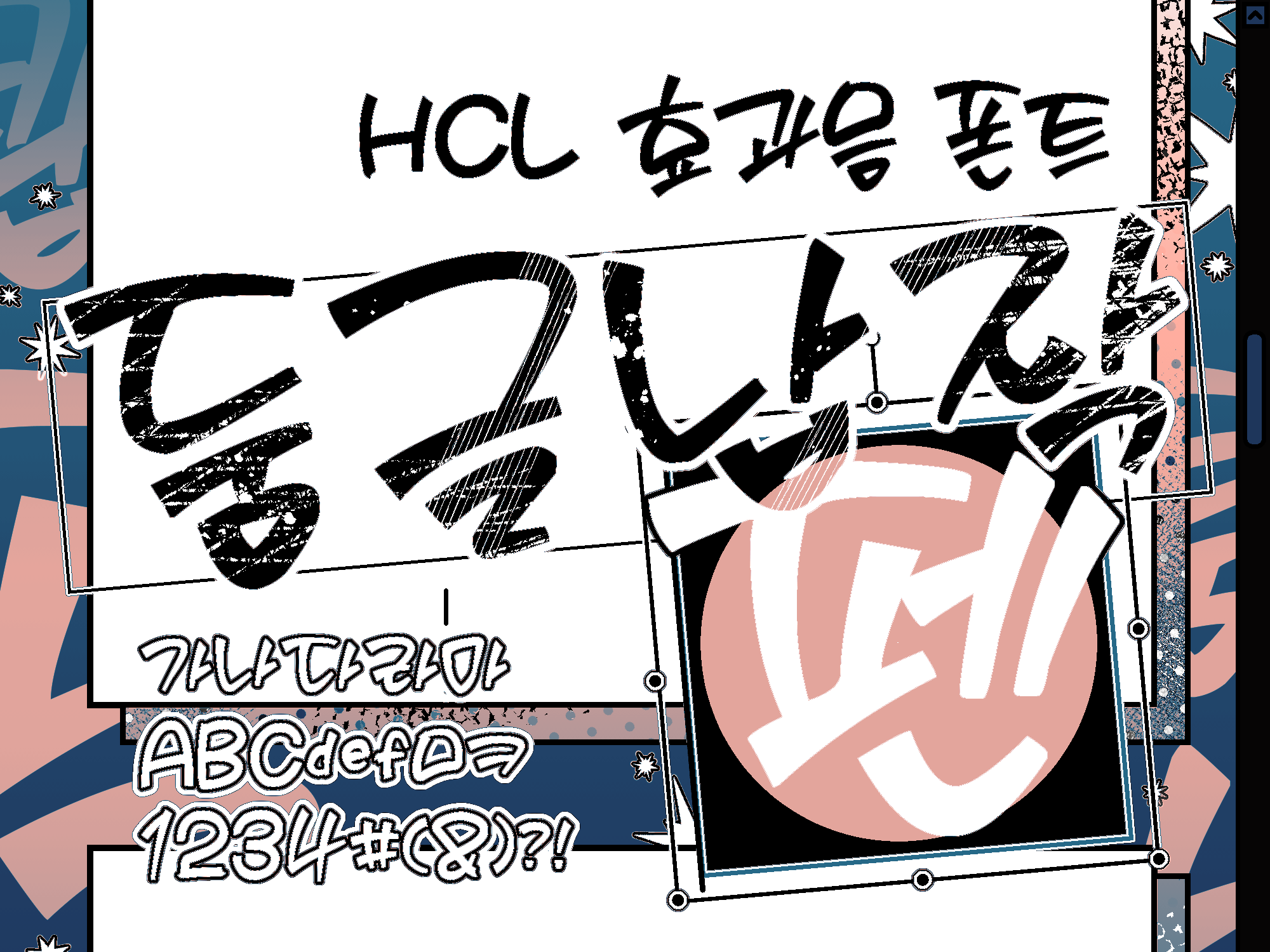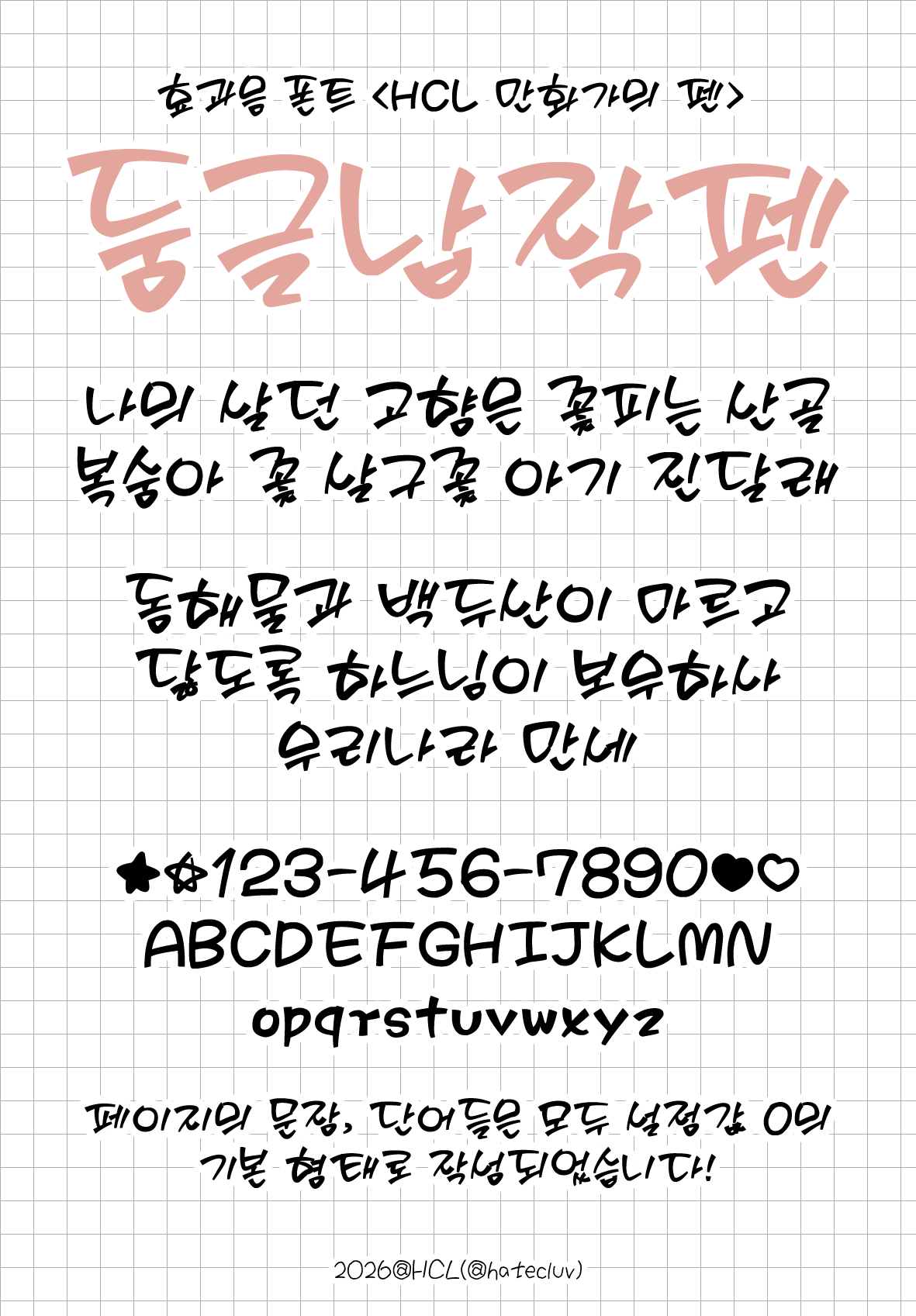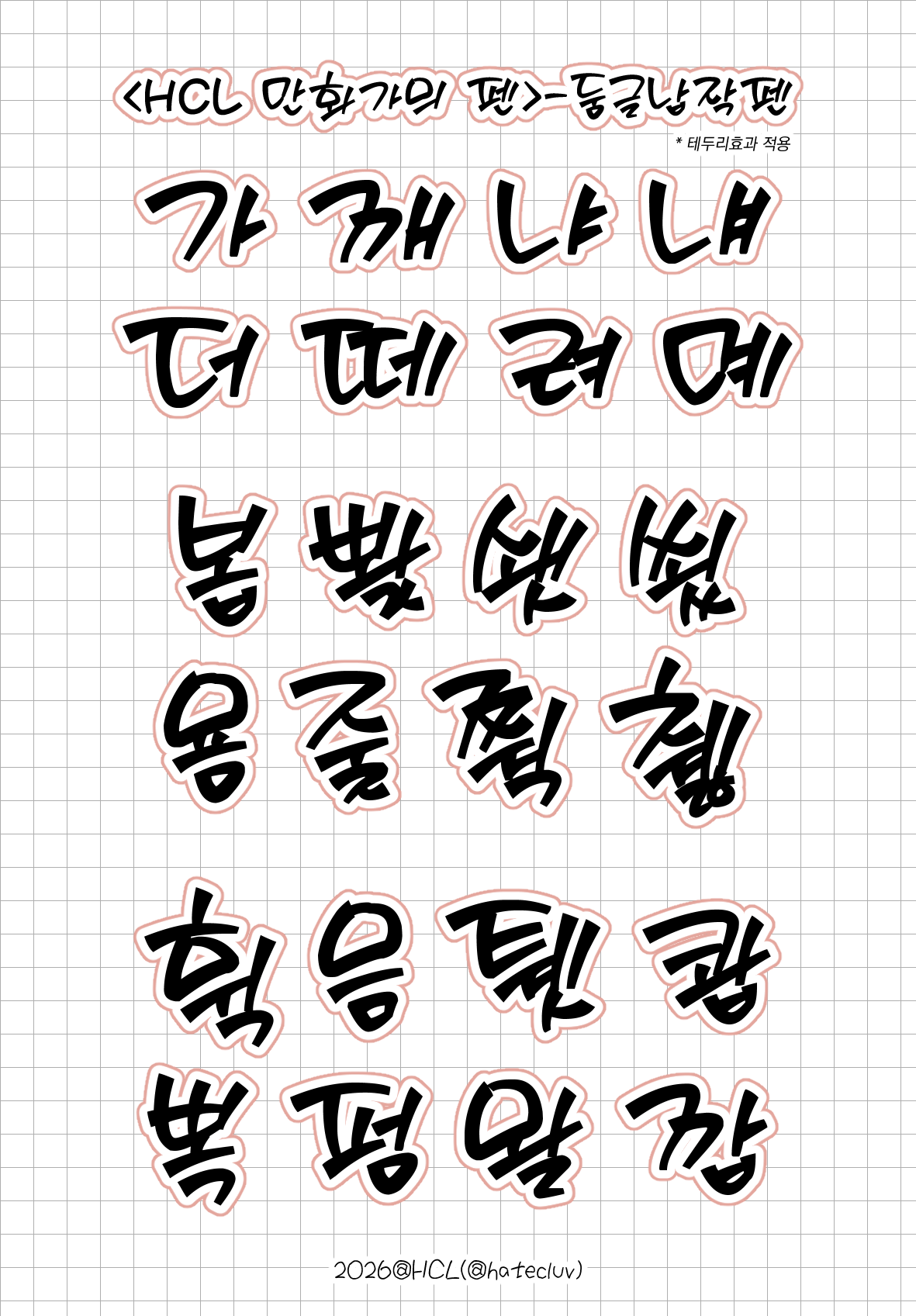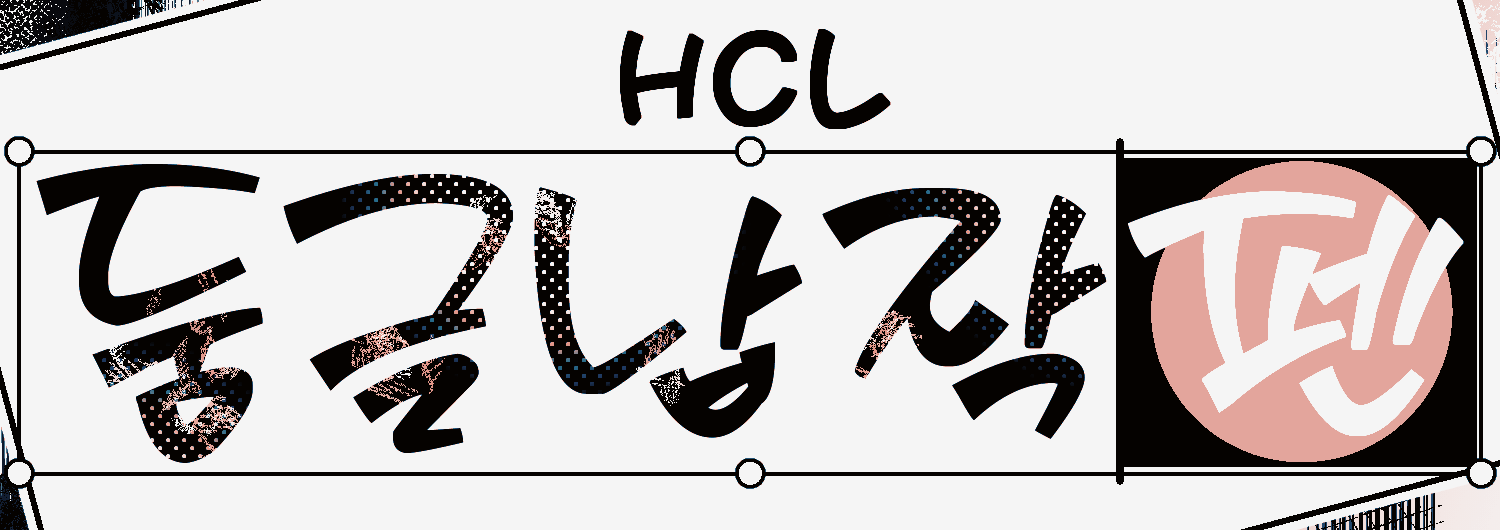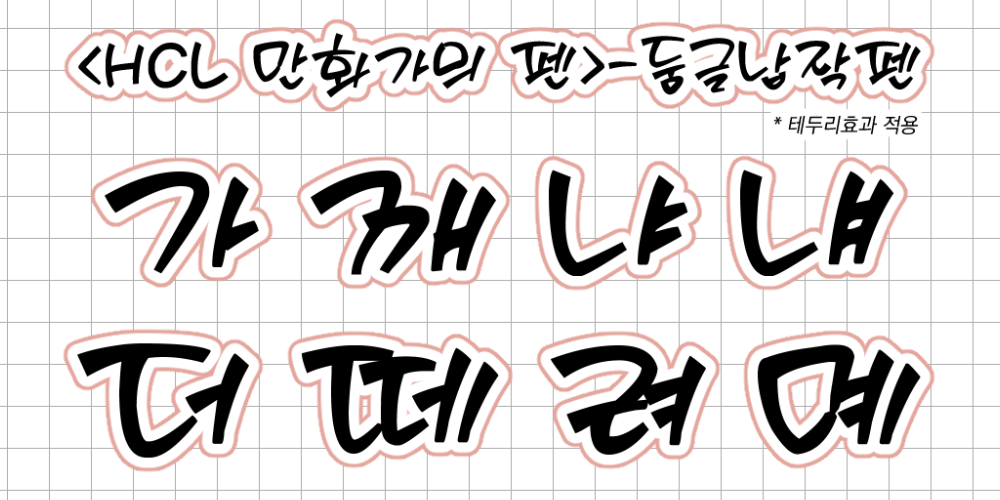
만화 효과음 느낌의 캘리그라피 폰트 5종 시리즈 <HCL 만화가의 펜> 중 <둥글납작펜> 입니다.
사각 팁 펜으로 쓴 듯한 굴곡진 손글씨 디자인으로 만화의 일상적인 장면과 효과음 대부분에 사용하기 좋습니다.
한글 조합 11172자 전체, 한글 기본 자모음(ㄱ,ㄴ,ㄷ,ㅏ,ㅑ,ㅓ...) 52자와 영문 대소문자, 숫자, 키보드 쉬프트 특수문자, ☆★♡♥, ©(카피라이트 문자) 등 추가 120글자를 지원합니다.